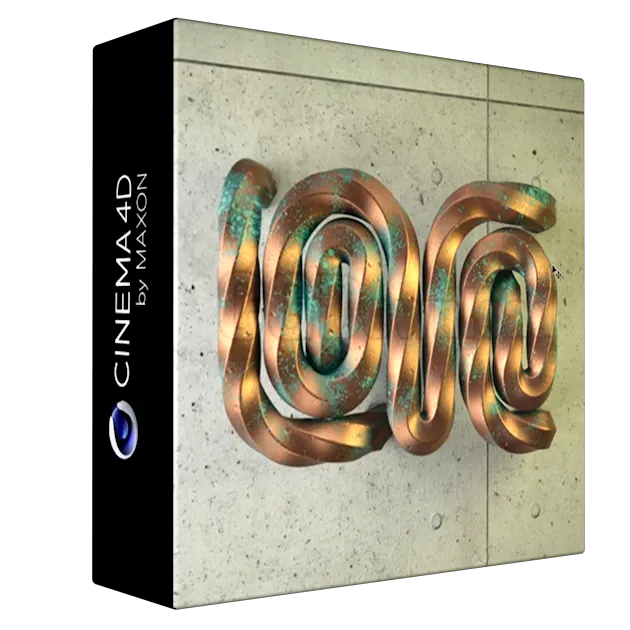
3D Font Design with a Metallic Finish
Изучите методы трехмерного моделирования в Cinema 4D, чтобы придать вашим надписям реалистичный и яркий вид.
В ходе изучения этих разделов вы научитесь создавать трехмерные буквы с металлическим блеском. Вы создадите три композиции в разных стилях моделирования и откроете для себя все приемы, позволяющие добиться блестящих и реалистичных надписей.